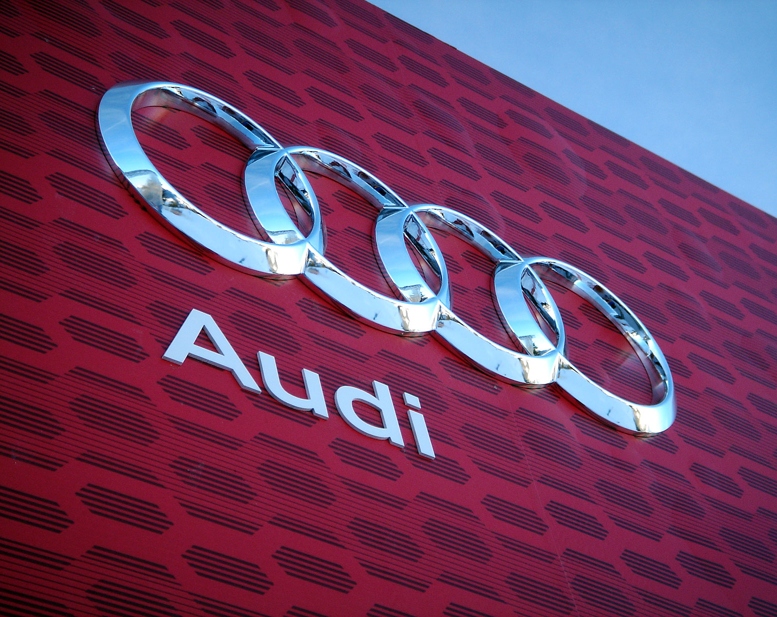
История логотипа Ауди: развитие и эволюция бренда | Дизайн, лого и бизнес
Ауди (Аudi) — крупная автомобилестроительная корпорация из Германии, являющаяся частью концерна Volkswagen Group. Машины, собранные на заводах Аudi, высокотехнологичны, надёжны и безопасны.
Предприятие было создано Августом Хорьхом в 1899 году. Спустя 11 лет бренд «Audi Automobil-Werke» («Автомобильный завод Ауди») выпустил первое транспортное средство.
Любопытно значение названия компании: слово «хорьх» переводится с немецкого языка как глагол «слушай». Размышляя над тем, как будут именоваться автомобили, основатель интересовался мнениями партнёров. Сын одного из них предложил перевести фамилию Хорьх на латынь — звучное и запоминающееся слово «Аudi» решили оставить.
Логотип Ауди: история создания и значение
Логотип Ауди в привычном виде разработан в 1932 году: Саксонский муниципальный банк способствовал объединению четырёх компаний (Audi, Horch, Wanderer и DKW), специализирующих сборке транспортных средств и изготовлении деталей для них.
Исходя из этого, на логотипе появились известные «сплетённые» кольца.
Производители не конкурировали между собой (у каждой марки была собственная «доля» рынка). Поэтому они стали единым целым, работали сообща.
Что означает логотип Ауди? — содействие и консолидацию. А четыре кольца на лого олицетворяют единство и сплоченность.
Первый логотип Ауди
В 1910 году появился первый логотип Ауди. На лого цифра «1» расположена на полусфере. Нижняя часть элемента находится за чёрным треугольником. При этом в фигуру вписана аккуратная прописная надписью «Аudi». Логотип выполнен в черно-белой расцветке.
История изменения логотипа Ауди
За время существования бреда использовалось 6 версий логотипов Ауди. Рассмотрим, как менялся знак Audi.
1932
1932 год — Ауди лого представляет собой четыре контурных тонких кольца, соединённых между собой. Внутри каждого кольца расположены эмблемы дружественных составляющих концерна (в том числе и та, что применялась в 1910 году).![]()
1949
1949 год — логотип Ауди становится более основательным. Теперь контур колец изображается ярче и имеет два слоя, между которыми есть пробел. Внутри иконки на вытянутом чёрном прямоугольнике расположена белая рубленая надпись «Auto Union». Текст выполнен заглавными буквами. Из внутренней части колец пропадают эмблемы компаний.
1969
1969 год — Ауди лого обретает прямоугольную форму. В фигуру вписываются слова «Audi NSU». Надпись выполнена белым цветом, массивным полужирным шрифтом. Прямоугольник заливается черным цветом. Также на логотипе теперь нет привычного элемента — сплетенных колец.
1985
1985 год — снова появляется изображение четырех колец. Но теперь они представлены в серебре. Под иконкой появляется надпись «Audi», выполненная округлым шрифтом. Цвет наименования также изменяется — становится ярко-красным.
2009
2009 год — слово «Audi» на логотипе приобретает малиновый оттенок. Кроме того, происходят изменения в положении надписи: теперь слово расположено слева под иконкой.
Дизайн колец становится более «легким».
Данный логотип сейчас можно встретить на продукции компании. Однако иногда на эмблеме наименование находится посередине, как это было на лого 1985 года.
Логотип Audi — символ качества и кооперации, взаимопомощи и поддержки. Он отражает богатую, насыщенную историю компании, но в то же время является по-настоящему современным, стильным, запоминающимся знаком.
Часто задаваемые вопросы
Когда появился первый логотип Ауди?Первый фирменный знак бренда Ауди появился в 1910 году.
Что означает логотип Ауди?Четыре кольца на знаке Ауди символизируют слияние четырех компаний: Audi, Horch, Wanderer и DKW.
Сколько раз менялся логотип Ауди?Логотип марки Ауди менялся 5 раз: в 1932, 1949, 1969, 1985, 2009 годах.
Как выглядит логотип Ауди?Логотип Ауди состоит из четырех последовательно переплетающихся колец и надписи «Audi» слева под символом.